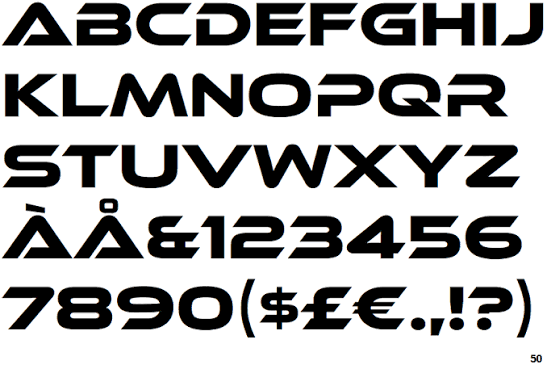
Nhiều phiên bản Ethnocentric Font trên Internet chưa được Việt hóa đầy đủ, dễ gặp tình trạng lỗi dấu tiếng Việt, sai ký tự hoặc các đường nét góc cạnh bị giảm độ sắc nét khi đưa vào thiết kế. Đặc biệt, khi phóng lớn để in trên hộp quà công nghệ, tem nhãn hoặc logo thương hiệu, các chi tiết hình học của font có thể bị ảnh hưởng nếu file không đạt chất lượng.
Font Ethnocentric là gì?
Ethnocentric là một phông chữ thuộc dòng Sans-serif mang đậm phong cách khoa học viễn tưởng và tương lai (Futuristic). Đặc trưng của phông chữ này là cấu trúc các ký tự rộng, phẳng và có các đường vát góc sắc sảo, gợi nhắc đến hình ảnh của các thiết bị công nghệ cao, robot hoặc ngành công nghiệp xe hơi. Đây là lựa chọn phù hợp cho các thiết kế logo công ty phần mềm, bao bì linh kiện điện tử, tiêu đề game hoặc các ấn phẩm truyền thông yêu cầu sự mạnh mẽ, bứt phá.
Ưu điểm của Ethnocentric nằm ở khả năng tạo dựng không gian thiết kế hiện đại và có độ nhận diện cao. Tuy nhiên, các bản gốc thường gặp vấn đề khi hiển thị các ký tự đặc thù như “đ, ư, ơ” hoặc các dấu thanh trong tiếng Việt. Bản phông Ethnocentric việt hóa được chia sẻ đã được xử lý kỹ lưỡng về mặt kỹ thuật, giúp các dấu nằm cân đối và hài hòa với các đường nét vát chéo của bộ chữ gốc, đảm bảo tính thẩm mỹ cao khi in ấn trên các chất liệu cứng như kim loại, nhựa sinh học hay giấy cao cấp.
Lưu ý: Font Ethnocentric có độ rộng ký tự lớn, do đó khi thiết kế bao bì hộp giấy, bạn nên tính toán khoảng cách dòng hợp lý để thông tin không bị chiếm quá nhiều diện tích bề mặt.
5 ứng dụng font Ethnocentric Việt hóa trong thiết kế và in ấn
Nhờ phong cách công nghệ, mạnh mẽ cùng các đường nét hình học đặc trưng, font Ethnocentric Việt hóa phù hợp với nhiều dòng bao bì, quà tặng và sản phẩm nhận diện thương hiệu hiện đại:
- Thiết kế bao bì thiết bị điện tử: Ethnocentric phù hợp để in tên thương hiệu trên hộp cứng đựng tai nghe, sạc dự phòng, phụ kiện công nghệ nhờ kiểu chữ góc cạnh, tạo cảm giác chuyên nghiệp và hiện đại.
- Khắc laser quà tặng kim loại: Logo sử dụng font Ethnocentric khi khắc trên bình giữ nhiệt inox, móc khóa hoặc phụ kiện kim loại giúp sản phẩm có điểm nhấn cá tính, phù hợp với phong cách công nghệ.
- Sản xuất set quà tặng công nghệ in logo: Font chữ này có thể ứng dụng trên sạc dự phòng, loa Bluetooth, chuột máy tính hoặc USB bằng kỹ thuật in UV, tạo sự đồng bộ cho bộ nhận diện thương hiệu.
- Thiết kế thiệp mời và backdrop sự kiện công nghệ: Các tiêu đề dùng Ethnocentric giúp chương trình ra mắt sản phẩm, hội thảo hoặc sự kiện doanh nghiệp thể hiện phong cách năng động, hiện đại.
- In túi giấy thương hiệu thời trang và phụ kiện: Sử dụng Ethnocentric cho logo hoặc slogan ngắn giúp bao bì tạo cảm giác mạnh mẽ, phù hợp với các thương hiệu hướng đến phong cách cá tính.
5 lưu ý khi sử dụng font chữ Ethnocentric Việt hóa
Để font Ethnocentric Việt hóa giữ được độ sắc nét khi đưa vào sản xuất thực tế, designer cần chú ý:
- Kiểm soát độ sắc của các góc chữ: Ethnocentric có nhiều chi tiết góc cạnh. Khi in trên bề mặt nhám hoặc kích thước nhỏ, cần kiểm tra khoảng cách giữa các ký tự để hạn chế tình trạng chữ bị dính hoặc mất chi tiết.
- Tối ưu đường Path khi gia công bế nổi: Chuyển đổi font sang dạng vector và xử lý các điểm neo giúp quá trình dập nổi logo trên hộp giấy diễn ra chính xác hơn, đặc biệt với các đường vát đặc trưng của font.
- Lựa chọn kích thước chữ phù hợp: Ethnocentric phù hợp với logo, tiêu đề hoặc slogan ngắn từ 2-5 từ. Không nên sử dụng cho đoạn văn bản dài vì cấu trúc chữ mạnh có thể làm giảm khả năng đọc.
- Kiểm tra màu sắc khi in UV: Các thiết kế công nghệ thường sử dụng màu bạc, đen, xám hoặc xanh đậm. Cần thiết lập hệ màu CMYK phù hợp để màu in trên sản phẩm gần với bản thiết kế.
- Điều chỉnh độ dày nét khi khắc laser: Với các chi tiết chữ nhỏ, cần cân chỉnh độ dày nét phù hợp để đường khắc trên kim loại, gỗ hoặc nhựa giữ được độ rõ ràng sau gia công.